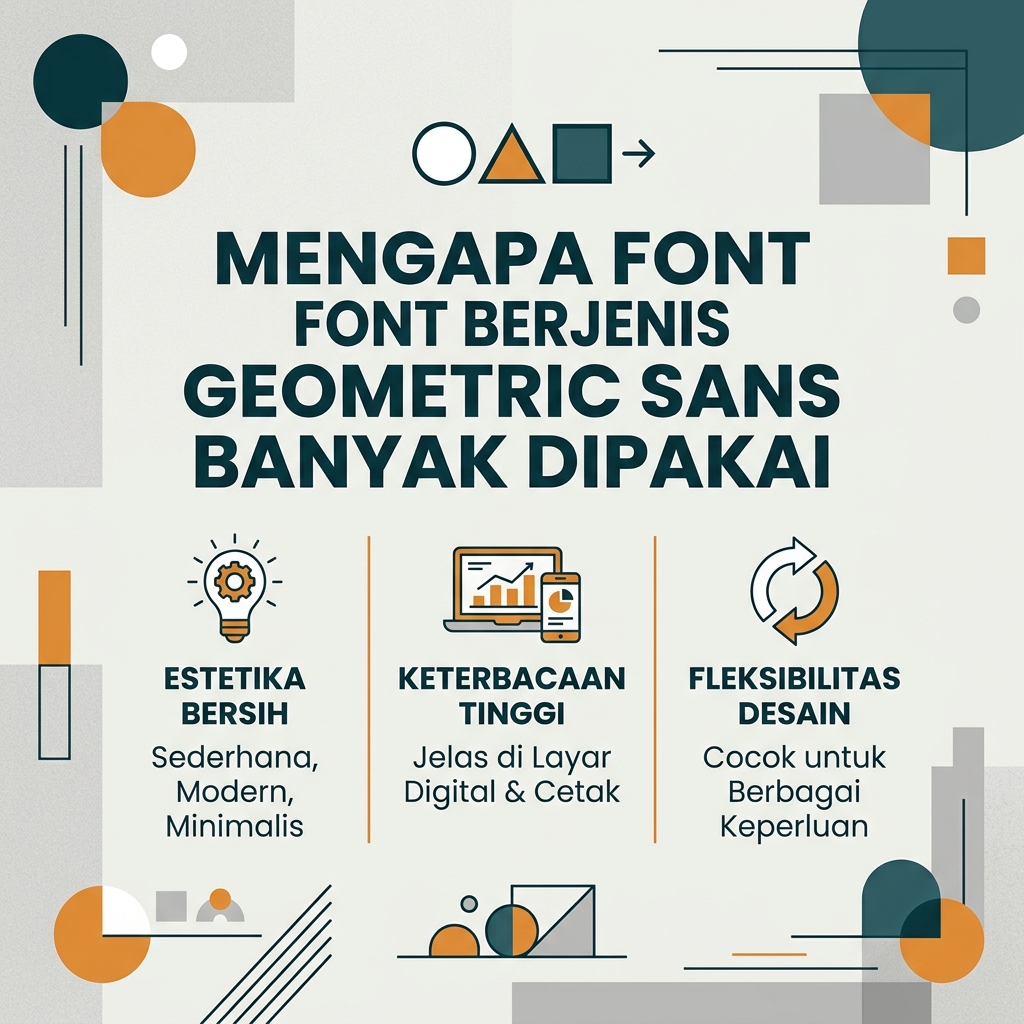
Gubuku – Usut punya usut, rahasia di balik tren logo “kembar” ini ada pada satu jenis font: Geometric Sans-Serif.
Tapi, kenapa sih font yang satu ini bisa mendominasi dunia desain dan bikin semua orang kepikat? Yuk, kita bedah alasannya sampai tuntas!
Apa Itu Font Geometric Sans?
Biar nggak bingung, mari kita kenalan dulu. Geometric Sans adalah rumpun font sans-serif (tanpa garis kait di ujung hurufnya) yang dibentuk berdasarkan bentuk-bentuk geometris murni, seperti:
-
Lingkaran sempurna (seperti huruf ‘O’ atau ‘C’)
-
Segitiga (terlihat pada struktur ‘A’ atau ‘V’)
-
Persegi dan garis lurus yang presisi
Contoh font Geometric Sans yang paling terkenal dan pasti sering kamu temui antara lain Futura, Montserrat, Century Gothic, dan Poppins.
5 Alasan Font Geometric Sans Sering Banget Dipakai
Bukan cuma ikut-ikutan tren, penggunaan Geometric Sans ternyata punya alasan kuat di baliknya:
1. Vibe-nya “Clean”, Minimalis, dan Estetik
Gen Z dan kaum milenial tuh paling demen sama visual yang aesthetic dan nggak ramai. Font Geometric Sans memberikan kesan yang clean, rapi, dan modern tanpa usaha berlebihan (effortless). Kurva lingkarannya yang presisi bikin mata betah melihatnya.
2. Super Enak Dibaca di Layar HP
Kita hidup di era scroll-scroll TikTok dan Instagram. Font dengan banyak dekorasi (serif) kadang suka kelihatan ruwet kalau ukurannya kecil di layar smartphone. Nah, Geometric Sans punya proporsi yang proporsional dan jelas, jadi tetap mudah dibaca (legible) meskipun di layar sekecil apa pun.
3. Terkesan Modern dan Futuristic
Karena dibuat berdasarkan prinsip matematika dan bentuk geometris dasar, font ini punya aura yang melompati zaman. Nggak heran kalau perusahaan teknologi, aplikasi, dan produk lifestyle kekinian senang banget pakai font ini biar terkesan inovatif dan up-to-date.
4. Fleksibel dan Serba Bisa (Versatile)
Mau dipakai buat judul brosur yang gede banget? BISA. Mau dipakai buat teks isi artikel yang panjang? BISA BANGET. Fleksibilitas inilah yang bikin para graphic designer malas berpaling ke font lain. Pake satu font family aja udah cukup buat bikin berbagai macam desain!
5. Efek “Blanding” Brand-Brand Mewah
Kamu pernah sadar nggak kalau logo Balenciaga, Saint Laurent, Burberry, sampai Spotify bentuknya makin mirip? Fenomena ini sering disebut Blanding (Minimalist Branding). Brand-brand ini sengaja pakai font Geometric Sans biar terlihat lebih inclusive, modern, dan relevan buat anak muda zaman now.
Kapan Sebaiknya Kamu Pakai Font Ini?
Buat kamu yang suka bikin konten, tugas presentasi, atau lagi bangun feed Instagram biar makin estetik, kamu bisa banget manfaatin font ini.
Buat Feed/Instastory: Pakai Poppins atau Montserrat (Bold) biar judul konten kamu langsung pop-up dan narik perhatian.
Buat Website/UI Design: Gunakan Inter atau Futura buat kesan yang profesional tapi tetap santai.